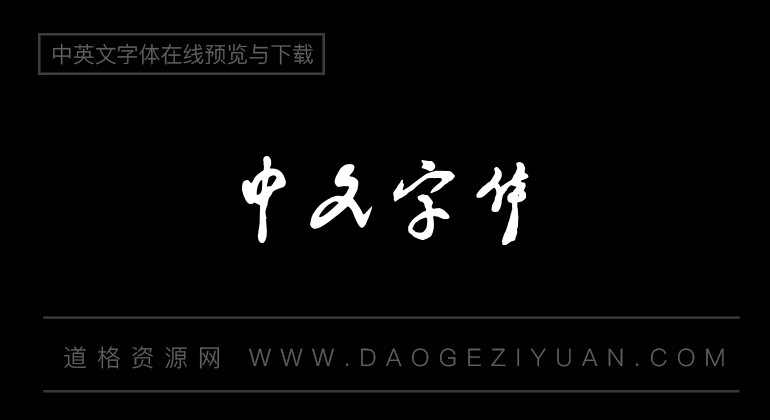
书体坊邓小平字体
书体坊邓小平字体是一款专为中国文字设计的简体字体。该字体由中国著名字体设计师邓小平设计,采用了邓小平所提倡的“简繁兼容”的设计理念,结合了繁体字形与简体字形的优点,极大地提升了中文文字的阅读体验。书体坊邓小平字体是一款由中国政府指定的官方字体,具有极高的可读性,可以满足中国文字的各种需求,是一款非常优秀的中文字体。
书体坊邓小平字体是一款非常不错的手写艺术字体,具有很好的视觉感,适合于文化类的宣传设计、商业类品牌的广告和产品包装设计以及个性化文字排版等较多场景。